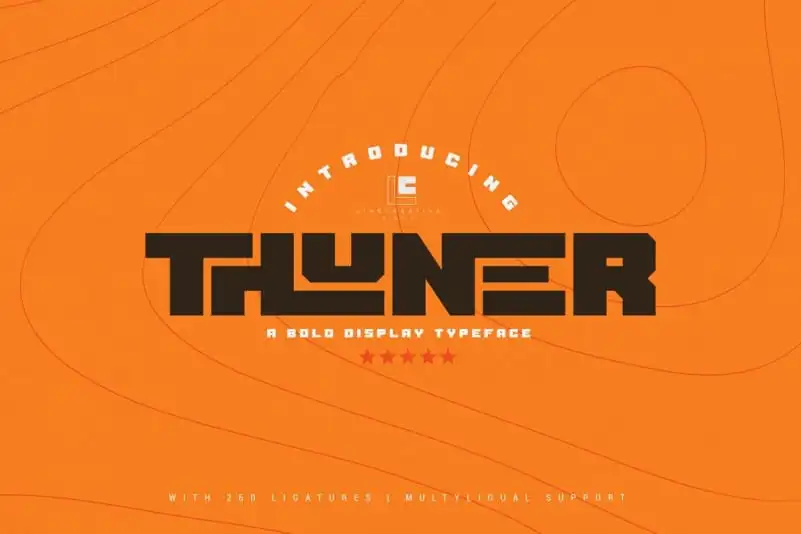
Descubra a Thuner Display Font, uma ótima opção para quem procura algo que destaque na sua próxima criação visual. Esta fonte é ideal para projetos divertidos e criativos, especialmente quando você está buscando uma aparição marcante em materiais de propaganda ou logotipos. Com um feixe de detalhes bold e agradáveis ao olho, Thuner oferece uma aparência atraente que torna qualquer projeto mais chamativo. O designer Linecreative criou essa fonte com uma característica inovadora: ligaturas. Ligaturas são combinações de letras que formam um único símbolo. Essa funcionalidade permite que você personalize suas criações de maneira única, seja em materiais impressos ou digitalizados. Ideal para a sua próxima camisa personalizada, logotipo de empresa ou arte em grande escala, Thuner é uma fonte robusta e divertida perfeita para qualquer design criativo!